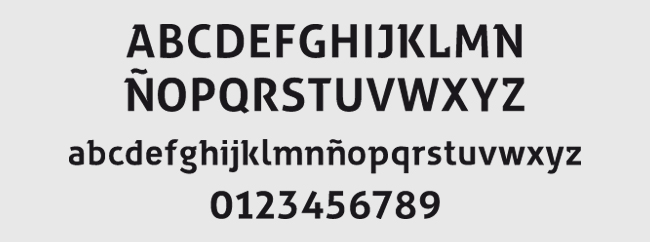
Tipografías gratuitas: Zwodrei ha sido diseñada por Lukas Bischoff <http://www.artill.de/> para la revista Neo2. Esta tipografía no se puede vender o regalar a terceros. El uso comercial de esta tipografía deberá incluir el siguiente texto legal: “La tipografía Zwodrei ha sido diseñada por Lukas Bischoff para la revista Neo2″.
Esta tipografía gratuita posee una especie de muesca hacia la izquierda en casi todos sus caracteres, tanto en caja alta como en caja baja. Es perfecta para titulares y subtitulares por su gran legibilidad y correcto tamaño.
Ha sido diseñada por Lukas Bischoff, un diseñador, ilustrador y director de arte alemán que tiene una multitud de proyectos en sus espaldas y en su portfolio.
Zwodrei typography designed by Lukas Bischoff <http://www.artill.de/> for Neo2 magazine. This typeface can’t be sold or given to anybody. The commercial use of this typography should always incluye: “Zwodrei typography designed by Lukas Bischoff for Neo2 magazine”.
This free typography has a subtle notch to the left in almost all its characters, both in uppercase and lowercase. It is perfect for headlines and subtitles due to its great readability and correct size.
It has been designed by Lukas Bischoff, a German designer, illustrator and art director who has a multitude of projects on his back and in his portfolio.